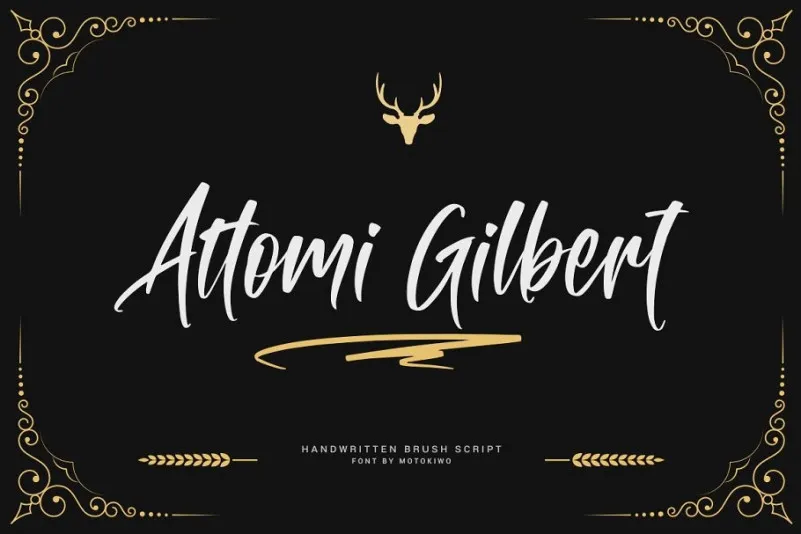
Attomi Gilbert Script Font – Download Grátis
A fonte ‘Attomi Gilbert Script’ é uma opção ideal para projetos que valorizam a sensação casual e descontraída do campo. Ela foi criada por M.0Type com um toque delicado, parecido com o movimento de traços da escrita à mão livre, embora produzido pela suavidade de uma canetinha. Este é perfeito para aqueles que buscam um ar elegante e autêntico em cada caractere, algo que pode ser usado tanto para projetos vintage quanto urbanos. Com seu design delicado e estilo atraente, esta fonte dispõe de muitas características interessantes, tornando-a uma opção versátil. Ideal para aplicativos de marca, panfletagem ou qualquer outro projeto onde você deseja dar um toque personalizado à sua criação. Ela traz uma sensação moderna e sofisticada sem perder o brilho e a autenticidade do design à mão, tornando-se uma escolha versátil para designers gráficos profissionais ou iniciantes em busca de novas ideias criativas.